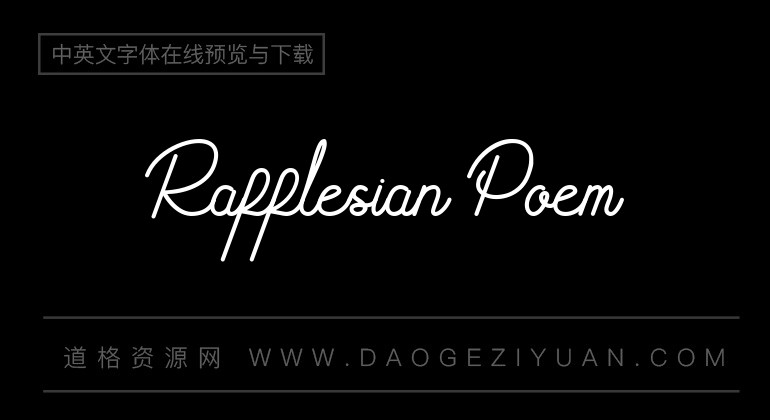
Rafflesian Poem 字体是一种结合了中英文字体特点的字体,它的设计来源于南洋拉菲尔斯(Raffles)的文字,以及英国殖民时期的印度文字。它的字体特点是有大小写字母,以及一些特殊符号,它的设计风格是简洁、精致、稳重,有着浓郁的古典风格,可以用于印刷、绘图、网页设计等。内容介绍
Rafflesian Poem是一款非常不错的手写艺术字体,具有很好的视觉感,适合于文化类的宣传设计、商业类品牌的广告和产品包装设计以及个性化文字排版等较多场景。